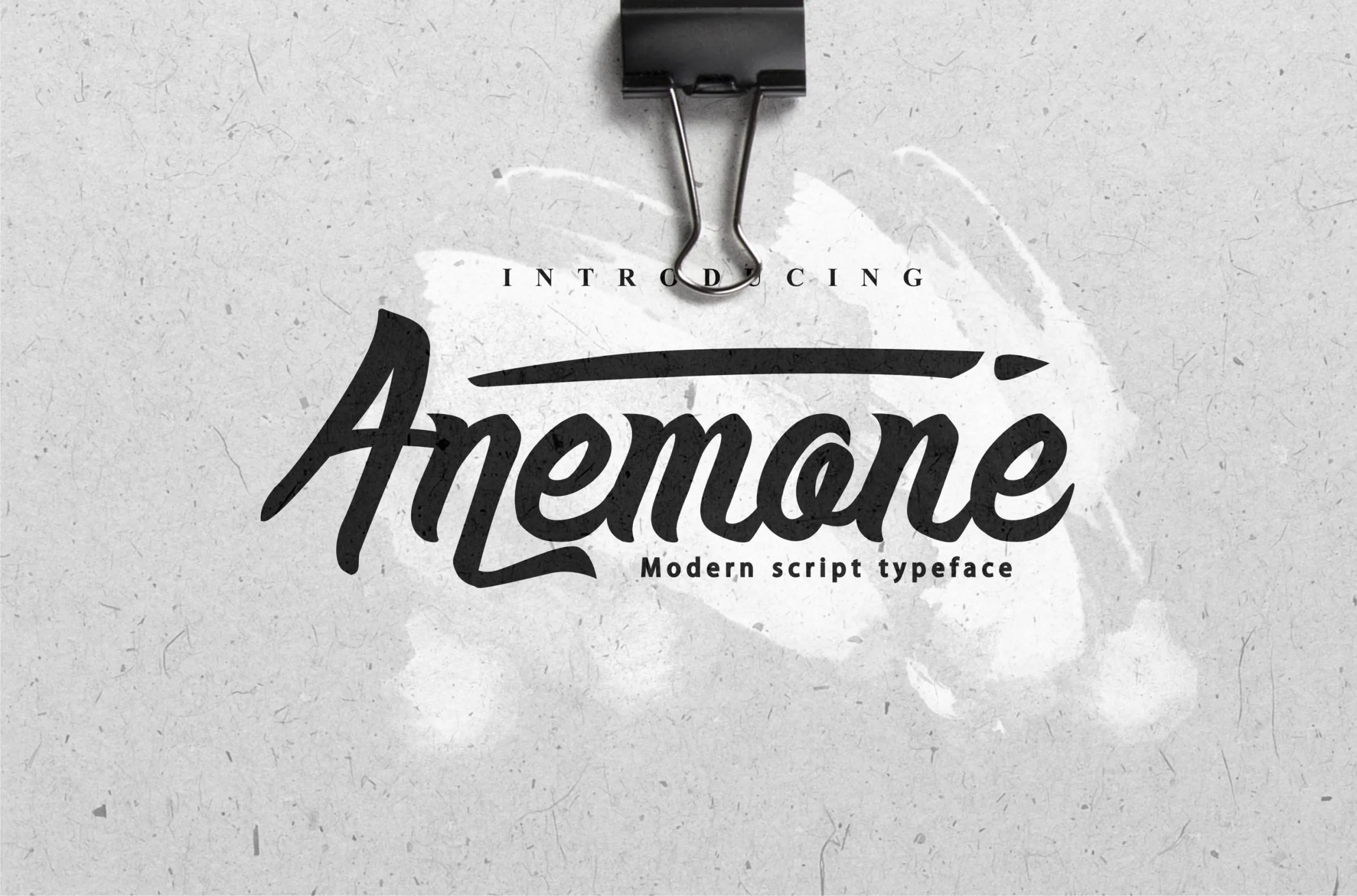
Anemone Script Font – Download Grátis
Anemone Script é uma fonte criada à mão que oferece diversas alternativas para tornar seu design único. Foi projetada especificamente com a finalidade de destacar os seus trabalhos e certificar-se de estar sempre na frente das tendências. Esta fonte atende perfeitamente tanto aos profissionais de logomarcas, quanto às empresas que buscam uma identidade única através de roupas ou materiais promocionais. Ela também é ideal para criações como cartazes, convites de festa e embalagens personalizadas. Cada caractere deste conjunto único foi projetado com o maior cuidado e atenção à detalhes feito à mão. É uma excelente escolha para quem busca uma fonte única que seja igualmente adaptável a uma variedade diversificada de projetos. Engane-se, nunca antes você teria tamanha oportunidade em sua disposição de criar um design inovador com esta fonte tão especializada e personalizável.